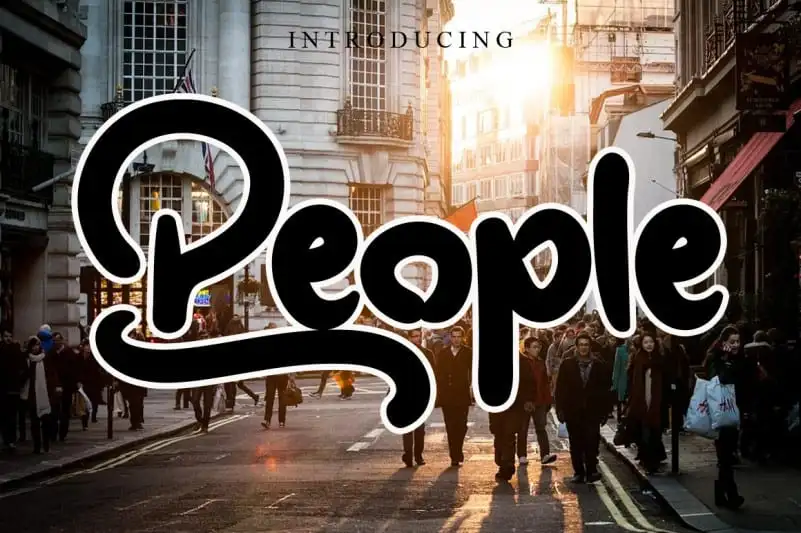
People Script Font – Download Grátis
People Script Font é uma fonte escrita a mão que transmite naturalidade, finura e suavidade. Inspirada na elegância dos traços delicados do idioma chinês, esta fonte tem um charme único que se adaptará perfeitamente a uma ampla gama de projetos. Seja para criar layouts sofisticados ou gráficos minimalistas, essa fonte adicionará um toque irresistível e distintivo aos seus trabalhos. Adaptable em qualquer design, People Script Font eleva o nível dos projetos sem esforço, tornando-o uma escolha ideal para designers em busca de algo singular que se adapte a múltiplos usos. Com seu designer experiente LevinCreative, é certo que você encontrará a fonte perfeita para seus projetos.